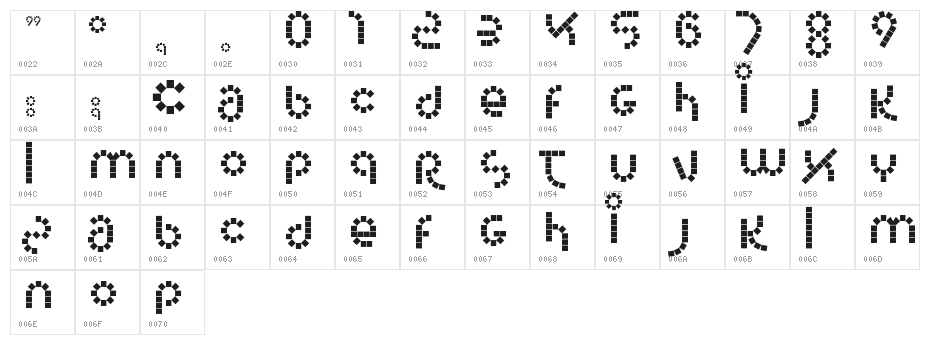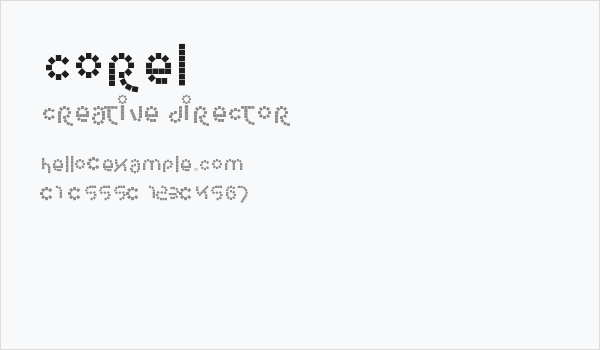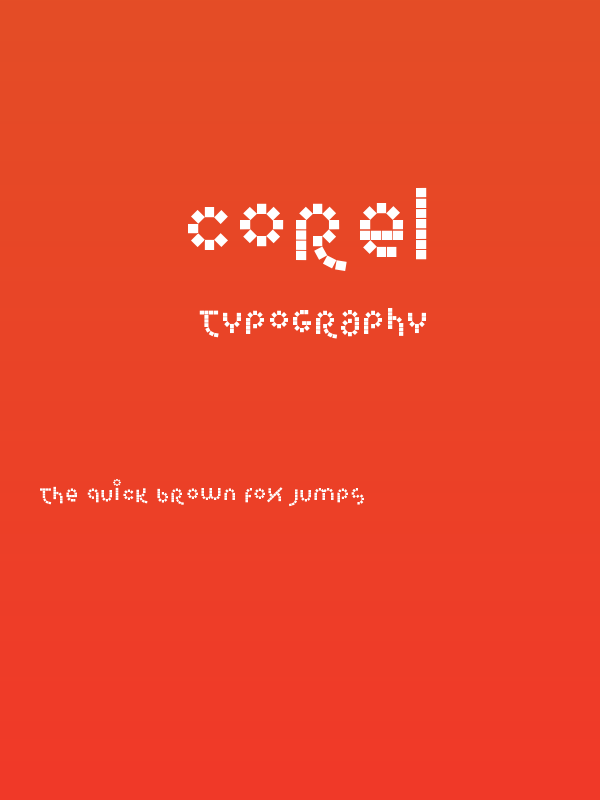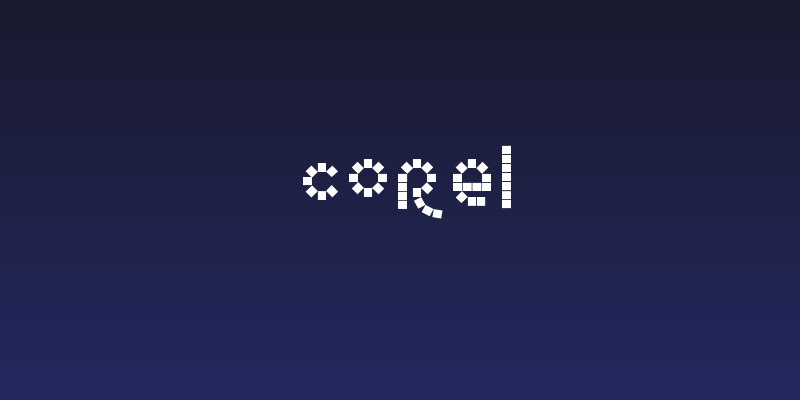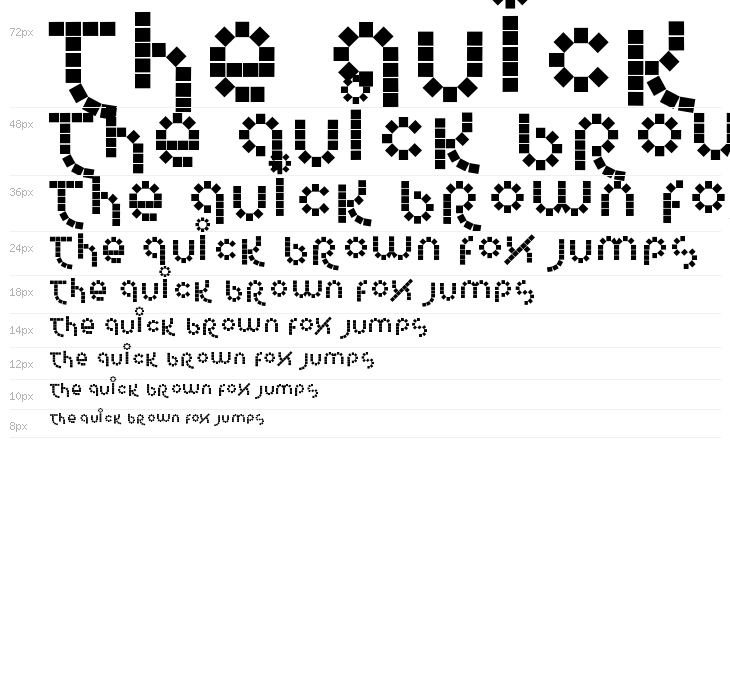
corel Font
| Caso d'uso | Decorative elements, Borders, Backgrounds |
| Progetti proposti | This pattern could be used for decorative borders, graphic design elements, or background textures. |